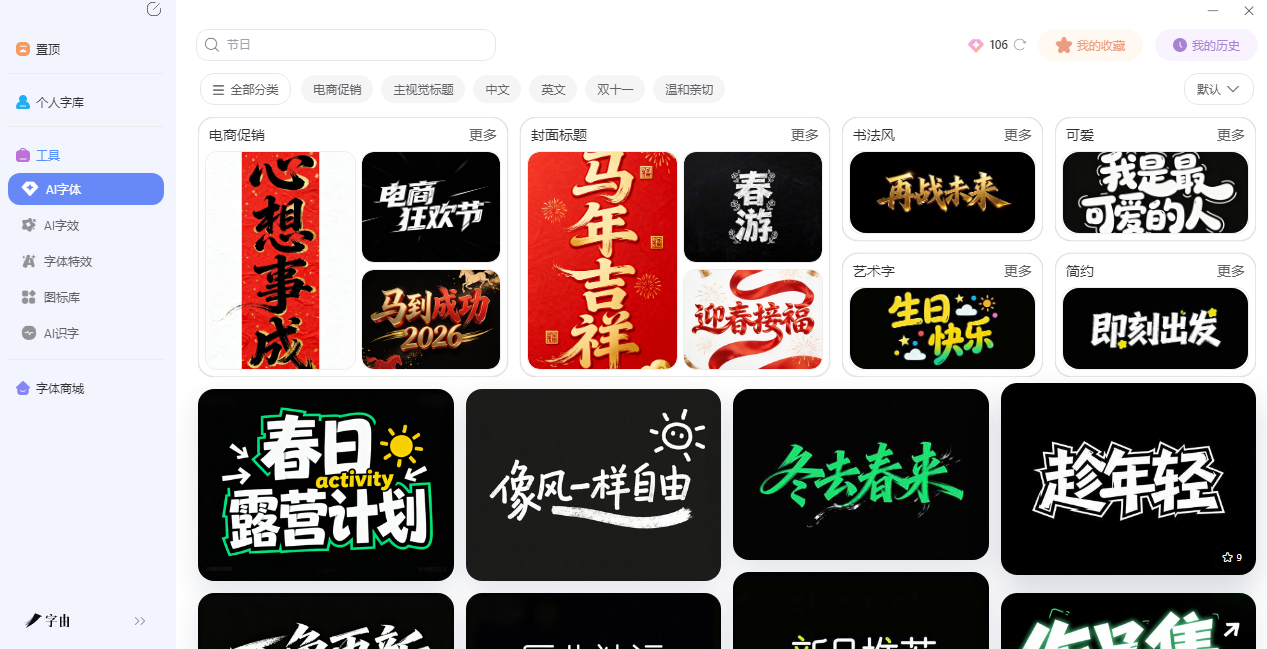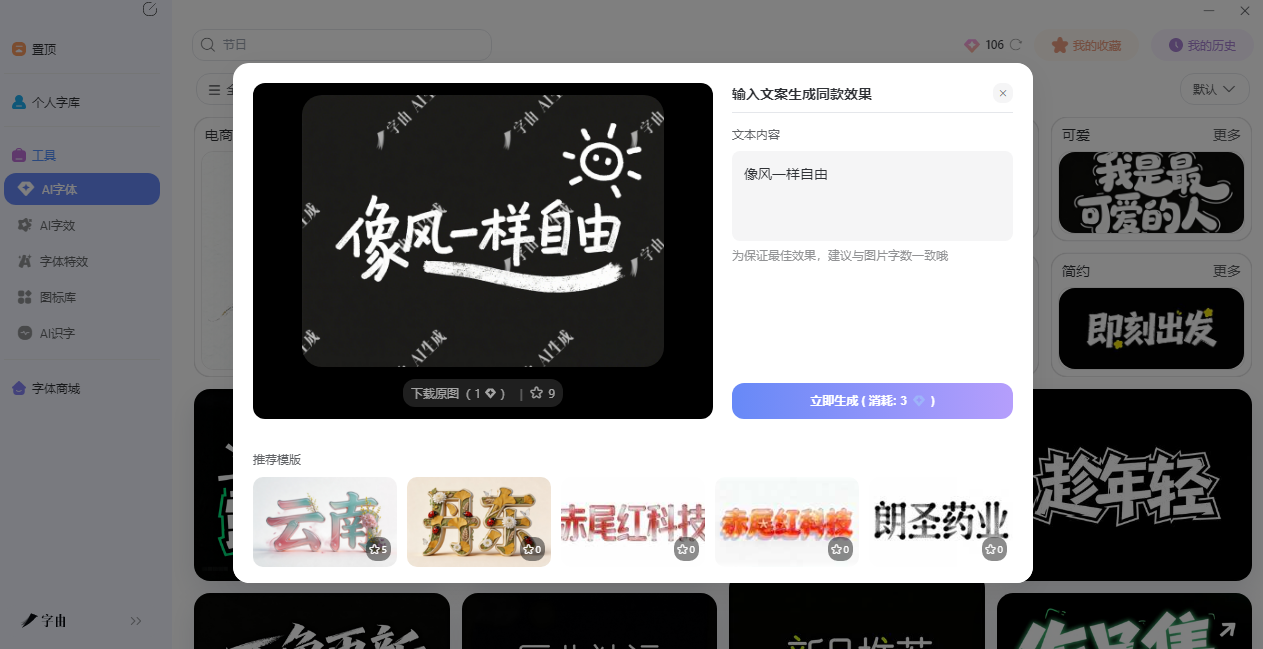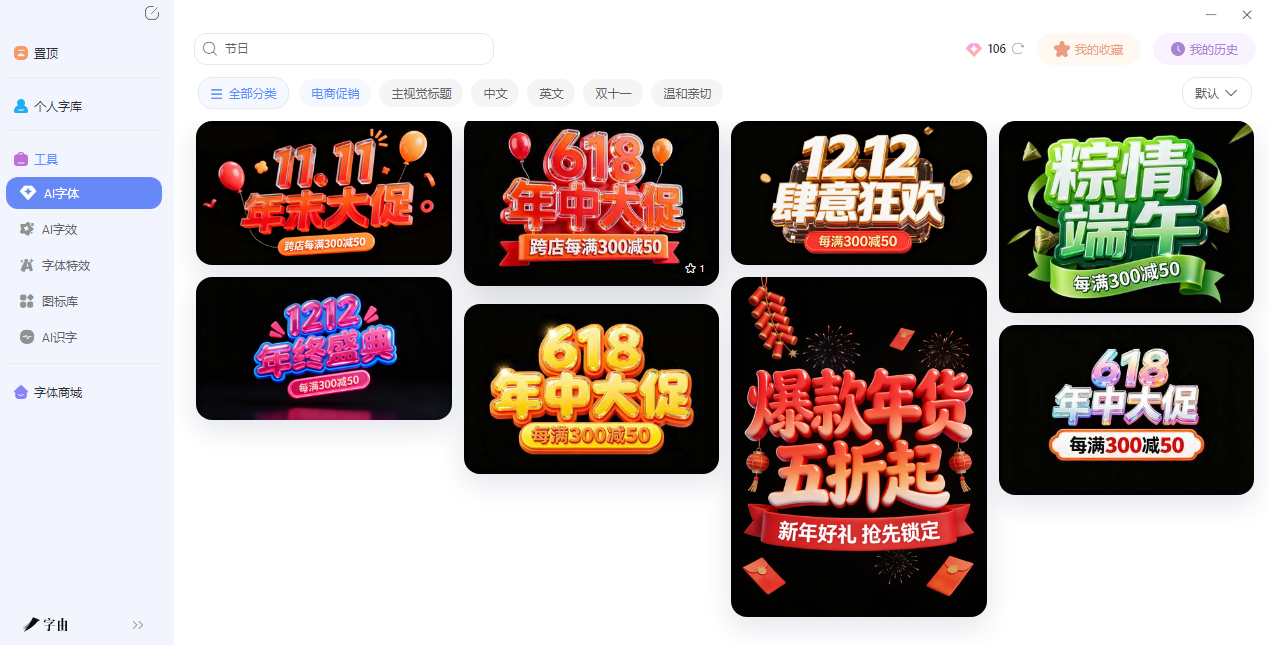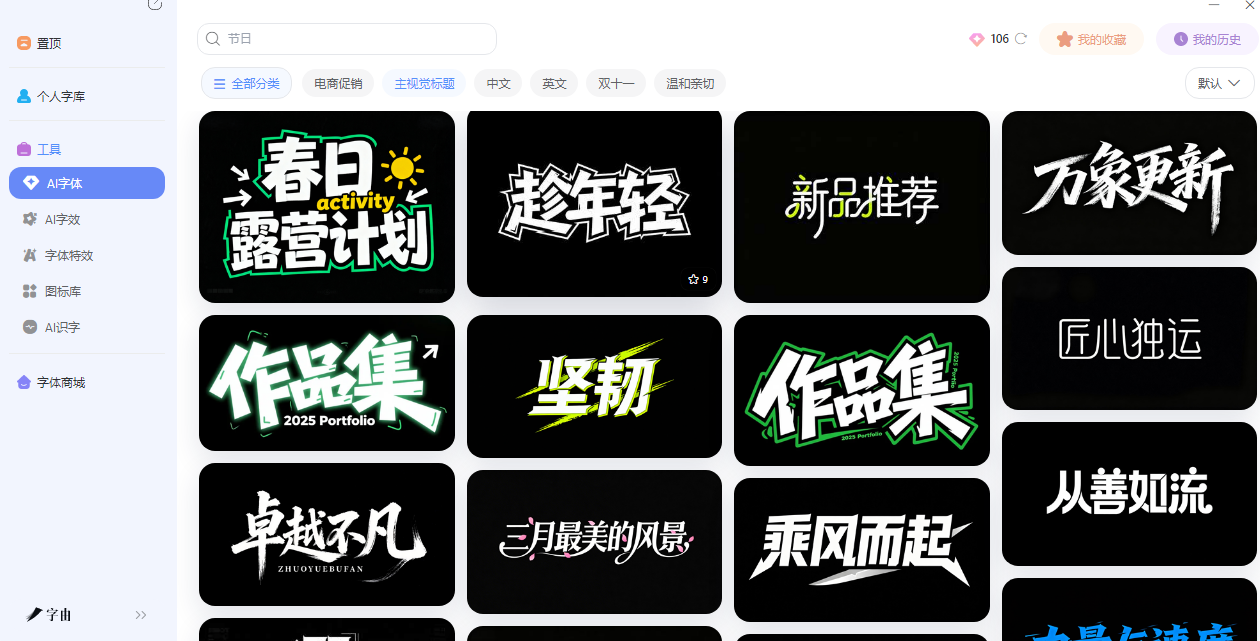
还在手动排版?文字图片生成器实测,10秒生成海报标题
做海报、做封面、做社交媒体配图的时候,我们经常会遇到字体融入不进去背景,又或者是字体效果还差那么点意思。自己再设计的话,肯定会增加工作量,并且效果也不一定好。但是现在只要有文字图片生成器,就可以很好地解决这个问题。不需要你懂什么建模、效果调整等原理,你只需要选个模板,改几个字,直接出图。今天我就拿字由的AI字体功能举个例子,从模板挑选到文案替换再到下载使用,每一步都介绍给大家,希望能帮到大家。
先来介绍一下字由(hellofont.cn),拥有大规模字体库,注册用户超过2000万,跟汉仪字库、蒙纳字库这些头部厂商都有深度合作。但很多人不知道的是,字由的“AI字体”功能,其实就是一个现成的文字图片生成器。打开字由官网或客户端,在顶部导航栏找到“AI工具”,点进去就能看到AI字体入口。界面非常直观——左侧是模板筛选区,中间是模板预览,右侧是文案输入框。
字由AI字体的核心逻辑是:选模板,换文案,一键生成。不需要任何设计基础,不需要打开PS,10秒左右就能拿到一张可直接使用的艺术字图片。这不就是大家想要的文字图片生成器吗?
2、AI字体模板库
字由的AI字体模板库相当丰富,足够日常设计使用。按场景分的话,模版有电商促销用的、新媒体封面用的、品牌标题用的、海报装饰用的。按风格分:有工整笔记风、潦草随笔风、书法手写风、霓虹光影、液态金属、国潮风、赛博朋克风等等。实际操作中,你可以直接用“分类”筛选器快速定位。比如要做一张国潮风的海报标题,在“风格”里选“国潮风”,所有相关模板一次性列出来,不用一页一页翻。每款模板都有预览图,鼠标悬停还能看动态效果。对于日常设计来说,字由AI字体的模板覆盖范围完全够用。文字图片生成器的核心价值就是“省时间”,不用从零开始调字体、调颜色、调阴影——模板里全都配好了,你只需要挑选喜欢的哪一款就行了。
那么接下来我会教大家如何使用AI字体这个工具。
3、AI字体使用教程
• 第一步:筛选模板。打开字由AI字体页面后,左侧有筛选栏。你可以按“场景”“风格”“语言”三个维度来筛选。举个例子,如果你要做一张618促销海报的标题,可以在“场景”里选“电商促销”,系统会列出所有适合促销场景的模板,然后根据你的品牌调性再微调筛选条件。
• 第二步:替换文案。找到合适的模板后,点击“生成同款”。页面右侧会出现一个文本框,把你自己的文案填进去。这里有一个小细节要注意:输入的字数不能超过原模板图片上的字数上限。因为每款模板的排版和字间距是固定的,超了的话画面会显得拥挤。
• 第三步:生成并下载。点击“立即生成”,等待5到8秒,系统就会生成一张带有你文案的艺术字图片。生成后可以直接下载PNG格式,背景默认是透明的,方便直接贴到海报或封面上。整个流程从打开页面到拿到图片,熟练了之后确实10秒左右就能完成。
4、其他使用注意tips
字由AI字体不是那种“生成即定稿”的工具。生成之后,如果觉得哪里不对,有几个调整选项:
重新生成:不满意当前结果,可以再点一次生成,AI会给出略有差异的效果。更换模板:如果发现选错了风格,可以直接返回模板库换另一个,文案不用重新输入。
下载格式:支持PNG格式下载,背景透明,方便直接叠加到其他设计素材上。
其实到这里,对于只想快速出图的用户来说已经十分足够了,这比起自己设计或者是去其他网站花钱购买来说完全是最佳选择。文字图片生成器的意义就在这里。
5、适合群体
字由AI字体这个文字图片生成器,适合以下几类人:
电商运营:每天要出大量促销海报,标题字需要够醒目、够有冲击力。用AI字体模板,10秒一张,效率翻倍。
自媒体创作者:封面图上的标题字决定了点击率。字由的模板库里有很多适合小红书、抖音封面的风格,直接套用就能出效果。
设计新手:不会用PS,不懂字体搭配,但偶尔需要做一张带艺术字的海报。字由AI字体就是为这种人准备的——不需要任何基础,选模板、改文字、下载,三步搞定。
经常做活动物料的设计师:品牌方临时要一张倒计时海报,没时间慢慢排版。打开字由,找到合适的促销模板,改一下日期和文案就可以了。